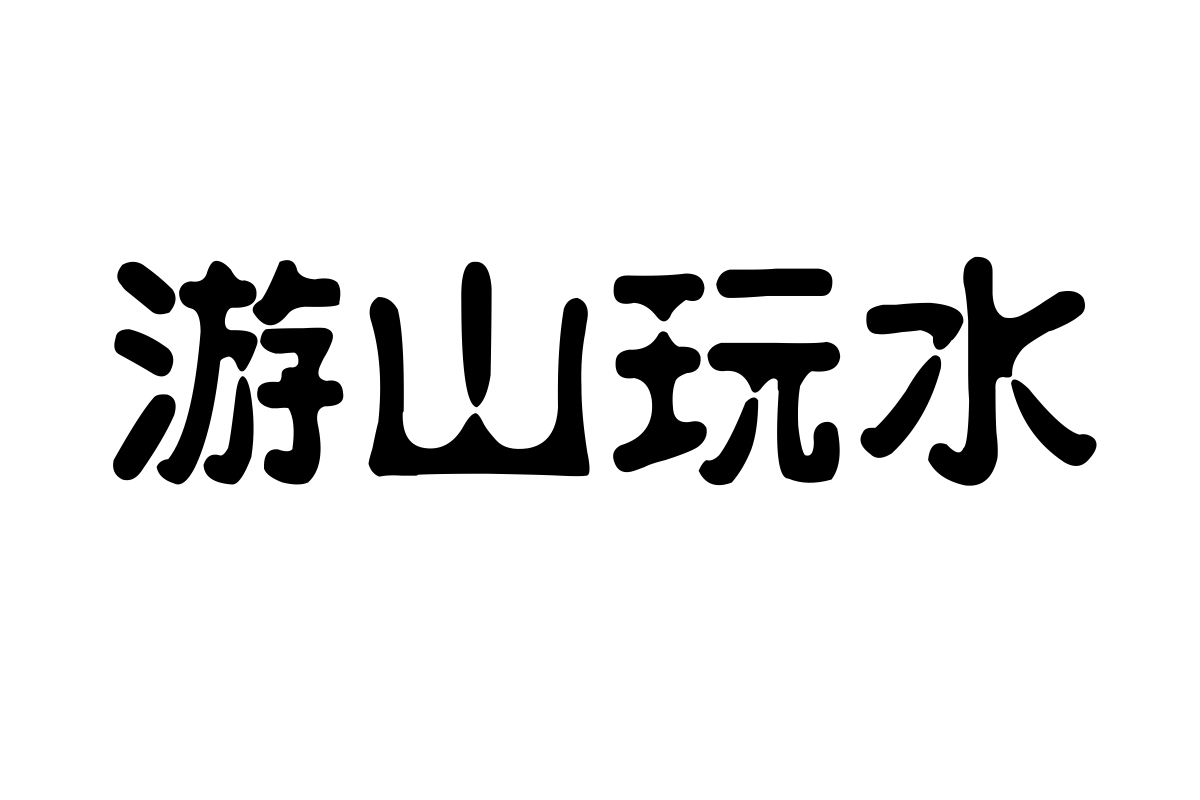
迷你简水柱是一款专为中文显示设计的字体,具有简洁、易读的特点。这款字体采用了独特的设计手法,将汉字的笔画进行了简化和重组,使得每个字都显得既清晰又易于识别。同时,该字体还注重了字形的稳定性和美观性,使得整个字体看起来既协调又有美感。
在迷你简水柱中,每个字的笔画都被巧妙地组合在一起,形成了独特的视觉效果。这种设计不仅使得字体更加美观,也使得字体在使用时更加流畅。无论是用于印刷还是电子显示,迷你简水柱都能展现出其独特的魅力。
此外,迷你简水柱还具有一定的可扩展性。通过调整字体的大小和间距,可以满足不同场景下的需求。这使得迷你简水柱成为了一款非常实用的字体,适用于各种场合。
总的来说,迷你简水柱是一款极具特色和实用性的字体,无论是从美观还是实用角度来看,都是值得推荐的字体选择。